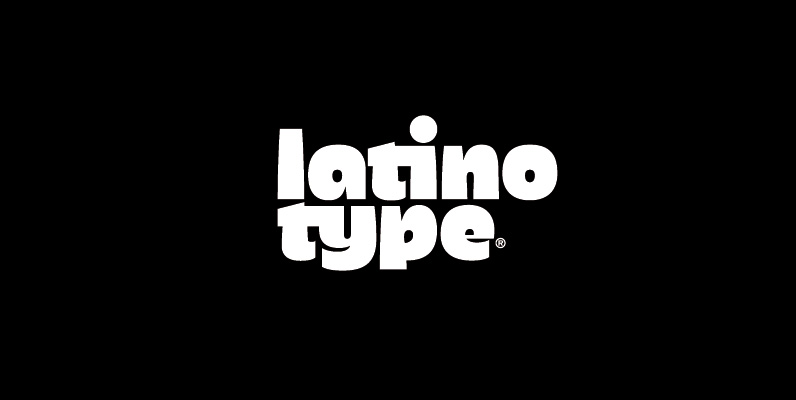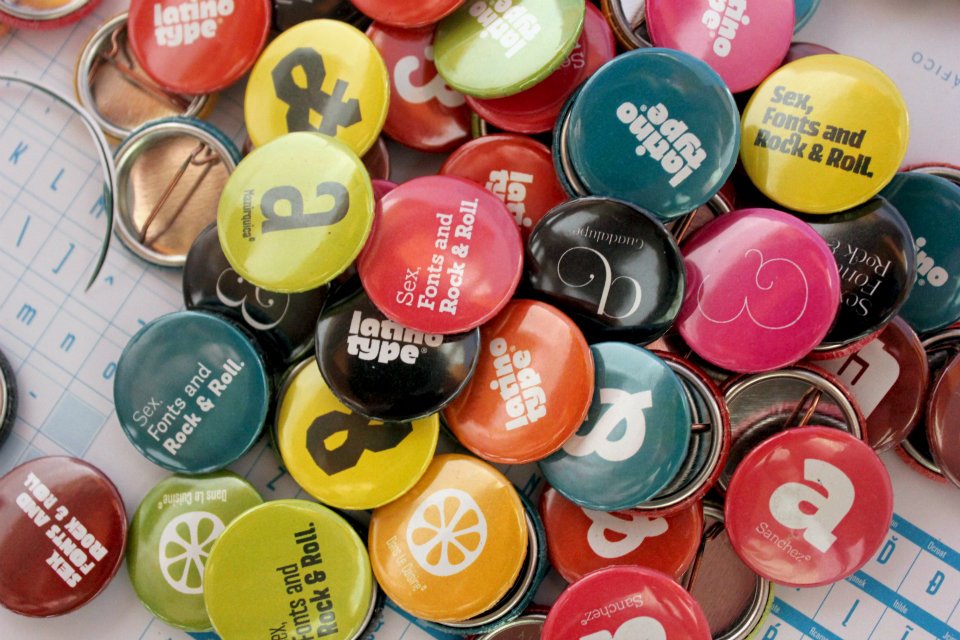
En el año 2003, en Talcahuano, Miguel Hernández comienza a dar los primeros pasos de lo que sería un largo camino en la disciplina tipográfica. Desde allí, empieza a comercializar sus fuentes píxel, inspirado por el trabajo de Susan Kare y las culturas precolombinas de Latinoamérica, en la extinta fundición Atomic Media y luego en Ultrafonts, con lo que resulta ser el primer chileno en cotizar sus fuentes en el extranjero. A través de su amigo Cristián González, Miguel conoce a Luciano Vergara en Concepción. Luciano, por su parte, con base en Santa Juana en el año 2005 y luego de cursar el Diplomado en Diseño de Tipografías de la Pontificia Universidad Católica de Chile, comienza a distribuir sus primeras fuentes display y para pantalla en la fundición T26.
En el año 2008, Luciano y Miguel deciden unir sus fuerzas y trabajar por un proyecto más ambicioso, que en ese momento tenía la finalidad de distribuir tipografía directamente desde Chile, de forma autónoma. Bajo esta consigna crean Latinotype, la primera fundición tipográfica chilena que logró posicionarse dentro del incipiente mercado de fundidoras latinoamericanas y crear conciencia en Chile acerca de la necesidad de profesionalizar la disciplina a través de la venta de licencias tipográficas de bajo costo.
En el 2010, después de un tiempo recorrido, Latinotype se reorganiza e integra a su equipo a Daniel Hernández, quien, con residencia en Maipú, después de haber pasado por el diseño de fuentes píxel en el año 2006, distribuía desde el 2010 sus fuentes a través de la fundición argentina Sudtipos. Los tres deciden dar un nuevo aire a la fundición y potenciar las ventas a nivel global. Es así como, a partir del año 2011, Latinotype cuenta con un catálogo de 16 fuentes, 3 familias display y una familia de texto. En un año, Latinotype ha logrado incorporar sus productos a 5 fundiciones, en las que sus fuentes obtienen excelentes resultados.